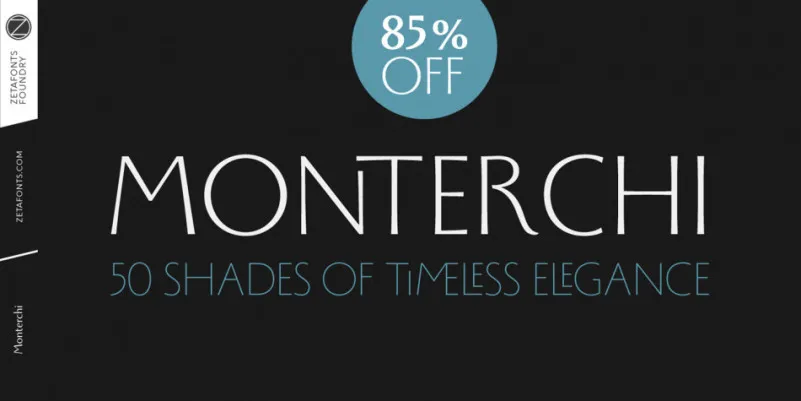
A Monterchi Font Family é uma bela tipografia ideal para destacar seu produto na categoria do design e lançamento de produtos. Inspirada no famoso fresco de madona grávida criado pelo pintor italiano Piero della Francesca em 1459, essa fonte representa um marco importante na história da arte renascença italiana. Em homenagem à esta obra icônica, o diretor de arte Riccardo Falcinelli do Zetafonts desenvolveu uma customização para a projeto em 2019, dando novo brilho e identidade visual ao artefato. Esta fonte é perfeita para destacar seu produto ou marca, tornando-a única e memorável, sem abrir mão da elegância e sofisticação associadas à renascença italiana. Com sua rica história e design único, a Monterchi Font Family oferece uma opção criativa para qualquer aplicação visual.